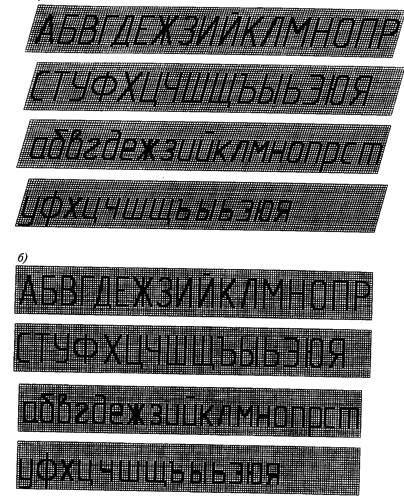
Шрифты чертежные
Чертежные шрифты, применяемые для нанесения всех надписей на чертежах и других технических документах, установлены ГОСТ 2.301-81. Чертежный шрифт содержит русский, латинский и греческий алфавиты, арабские и римские цифры, а также знаки.
Размер шрифта h определяется высотой прописных букв, мм: 2,5; 3,5; 5; 7; 10; 14; 20; 28; 40.
Типы шрифтов:
тип А без наклона (толщина линий шрифта d=1/14 h);
тип А с наклоном около 75o (d =1/14 h);
тип Б без наклона (d =1/10 h);
тип Б с наклоном около 75o (d =1/10 h).
Построение шрифта русского алфавита во вспомогательной сетке показано на рис. 6 (тип А) и рис.7 (тип Б).
Рис. 6
Рис. 7